求职季总是让人既期待又紧张,对不对?我们都希望自己的简历能在众多竞争者中脱颖而出,抓住面试官的眼球。但你有没有想过,除了内容和排版,一个小小的字体选择,其实也藏着大学问,甚至能悄悄影响HR对你的第一印象!我最近在帮朋友们修改简历时就发现,很多时候,一个不合适的字体,真的会让简历瞬间“掉价”,显得不够专业,甚至让人觉得你做事不够细致。反之,选对了字体,简历的整体质感立马提升好几个档次!这可不是我凭空想象哦,这是我从无数简历筛选和面试经验中总结出来的“血泪教训”。在这个快节奏的时代,HR们浏览一份简历可能就几秒钟,如果你的字体选择能让他们感到舒服、清晰,那就是你成功的第一步!现在市面上流行的字体五花八门,到底哪些字体既符合最新的职业趋势,又能展现你的专业度呢?别担心,今天我这个“过来人”就来给大家深入解析,教你如何避开雷区,选出那个能让你的简历瞬间“高大上”的“神仙字体”!保证你读完这篇,立刻就能动手优化自己的简历,提高成功率!下面就让我们一起,准确地了解如何通过字体选择,让你的简历在众多竞争者中脱颖而出,离梦想的offer更近一步吧!
字体选择:你的“无声名片”到底有多重要?
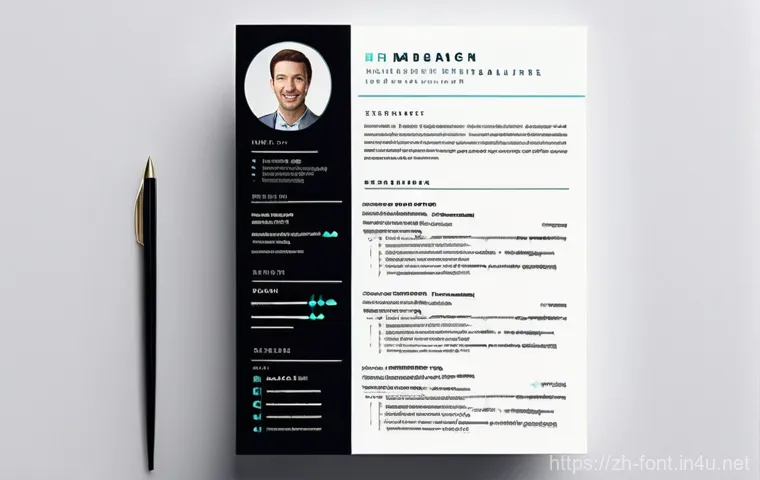
字体:你给HR的“第一印象”
亲爱的朋友们,你们有没有想过,一份简历投递出去,HR扫一眼可能就几秒钟?在这短短的时间里,除了你的内容,还有什么能瞬间抓住他们的目光,让他们愿意多停留几秒?我跟你说,字体!对,就是这个看似不起眼的小细节,它就像你的“无声名片”,默默地传递着你的专业度、品味,甚至是你对这份工作的重视程度。我有个朋友小李,能力明明很强,每次投简历却总石沉大海。后来我帮他一看,好家伙,简历上的字体五花八门,有卡通的,有艺术的,整个版面乱糟糟的,看得人眼花缭乱。我当时就跟他说,你这样投简历,HR第一眼就会觉得你不够严谨,甚至对工作缺乏基本的尊重。这可不是我胡说,这是我这些年看了无数简历,以及跟好几位资深HR朋友聊过之后得出的“血泪教训”啊!
别小看这些“小细节”:它藏着你的专业度
很多人觉得,字体不就是好看不好看嘛,内容才是王道。这话没错,内容当然重要,但是!如果你的“门面”就没收拾好,HR可能根本没兴趣深入了解你的“内涵”!你想想看,如果你收到一份字体模糊、大小不一、看着很费劲的简历,你会怎么想?是不是下意识就觉得这个人可能不太注重细节,做事有点随意?反之,一份排版整洁、字体清晰、阅读舒服的简历,哪怕内容暂时还没来得及细读,但第一印象就已经赢了。这背后传递的信息是:你是一个认真细致、有条理、注重专业形象的人。特别是在现在这个竞争激烈的求职季,每一个能让你脱颖而出的细节,都弥足珍贵。所以,选对字体,绝不仅仅是让简历“好看”那么简单,它更是一种无声的自我营销,帮你给HR留下一个专业且值得信赖的形象。
那些年我们踩过的“字体雷区”,你中招了吗?
“避之不及”的“非主流”字体
我们年轻人嘛,都喜欢追求个性,希望自己的简历能与众不同。但个性化和专业度之间,真的要找到一个微妙的平衡点。我见过太多朋友,为了“突出个性”,把简历弄得花里胡哨,用上各种奇奇怪怪的艺术字体,比如什么华文彩云、方正卡通、或者那种手写体。说实话,我自己看着都头疼,更别说每天要看上百份简历的HR了!这些字体虽然可能很“潮”,但它们最大的问题就是:阅读困难!你想想,HR是在高效筛选人才,不是在欣赏艺术品。如果你让他们的眼睛需要费力辨认每一个字,那你的简历很可能就会被毫不留情地刷掉。我有个朋友,学设计的,他想在简历里展现自己的创意,结果用了几种非常独特的字体。虽然他能力很强,但投出去的简历面试机会寥寥无几。后来我让他换回了常规的专业字体,面试机会一下子就多了起来。这就是活生生的例子,很多时候,你的“小心思”可能适得其反哦!
别让“艺术感”毁了你的专业度
除了那些过于花哨的艺术字体,还有一类字体也常常被我们“误用”,那就是一些系统自带的、显得有些老旧的字体,比如纯中文环境下的宋体。虽然宋体很经典,但在简历中,它会显得过于传统,缺乏现代感,不能很好地展现你的活力和与时俱进。当然,如果你应聘的是非常传统、严肃的行业,比如学术研究、文化遗产保护等,宋体或许还有一丝容身之地。但对于大部分现代企业,尤其是互联网、金融、科技、快消等行业,宋体真的会让你显得有点“落伍”。我真心建议大家在选择字体时,宁愿选择“平庸”的专业,也绝不要“出位”的业余。记住,简历是你的求职武器,它的首要任务是高效、清晰地传递你的信息,而不是展现你的字体收藏。下面我给大家整理了一个小表格,列举了一些常见的字体“雷区”和我的建议,希望大家都能避开这些坑:
| 字体类型 | 常见问题 | 建议 |
|---|---|---|
| 花哨艺术字体 (如:华文彩云) | 阅读困难,缺乏专业度,显得不成熟。 | 除非是设计类简历,否则坚决避免。 |
| 默认/系统老旧字体 (如:宋体/Times New Roman (纯中文环境)) | 缺乏现代感,略显沉闷和保守,无法突出个性。 | 可用现代感更强的无衬线体替代。 |
| 过小或过大的字体 | 过小易造成阅读疲劳;过大显得排版粗糙,浪费空间。 | 正文建议10-12pt,标题14-16pt。 |
HR眼中加分的“王牌”字体,你知道几个?
清晰易读:简历字体的“黄金法则”
既然知道了哪些字体不能碰,那我们接下来就得聊聊,到底哪些字体才是HR们真正喜欢、甚至能给你的简历加分的“王牌”选择。我的经验是,无论你应聘什么职位,清晰易读永远是简历字体的“黄金法则”。想象一下,HR每天要处理大量的简历,他们最需要的就是一眼就能抓住重点,快速获取信息。所以,那些笔画清晰、结构稳定、辨识度高的字体,自然会成为首选。在中文简历中,我强烈推荐大家使用微软雅黑、思源黑体(Noto Sans CJK)和方正兰亭黑。这几款字体都是现代感十足的无衬线字体,字形简洁大方,在屏幕上和打印出来都非常清晰。我之前帮好几个朋友改简历,仅仅是把字体统一成微软雅黑,整个简历的专业度就瞬间提升了好几个档次,他们自己都惊叹效果这么明显!
国际范儿与本土化:中英文字体搭配秘籍
对于有英文内容的简历,或者需要展现国际范儿的求职者来说,中英文字体的搭配就显得尤为重要了。很多时候,我们会直接用一个中文字体,然后英文部分就跟着一起变,结果不是英文看着别扭,就是中文显得不协调。其实,最理想的做法是为中文和英文选择各自最合适的字体,并且确保它们风格统一。英文部分,我通常推荐使用Arial、Calibri、Lato、Open Sans或者Roboto。这些都是非常经典的无衬线字体,简洁、专业、易读,而且在国际上通用度很高。比如,你可以选择中文用微软雅黑,英文用Calibri,它们都是现代无衬线体,搭配起来非常和谐,看起来就像是精心设计过的一样。我记得有一次,我参加一个跨国公司的招聘会,当时就听到HR提到,他们更偏爱那些中英文排版统一、看起来“舒服”的简历。所以,别小看这个搭配,它可是能悄悄帮你加分,让你在国际化的背景下也显得游刃有余!
字体大小和行距:别让“视觉疲劳”拖垮你的简历
大小适中:简历阅读舒适度的秘密
选对了字体,这只是成功的第一步。接下来,字体的大小和行距,这两个细节,同样能决定你的简历是让人“赏心悦目”还是“望而生却”。我发现,很多朋友在排版简历时,要么字号太小,密密麻麻挤成一团,让人看得眼睛疼;要么字号太大,几句话就占满一页,显得内容空洞,不够充实。这两种情况都会给HR带来视觉疲劳,甚至觉得你不懂得如何合理利用空间。我的建议是,简历正文的字体大小一般选择10到12pt(磅)为宜。这个尺寸在大多数屏幕和打印件上都清晰可辨,既不会太小导致阅读困难,也不会太大显得笨拙。当然,你的姓名、联系方式这些重要信息,以及各个板块的大标题,可以适当放大一点,比如14到16pt,这样能更好地突出重点,让HR一眼就能抓住关键信息。我曾经帮一个朋友调整简历,他原本的字号统一都偏小,我给他调整了合适的字号,并把重要信息加粗放大,他再看自己的简历,都觉得瞬间变得清晰明朗,阅读体验好了不止一星半点!
行距与段落:打造“呼吸感”的版面
除了字体大小,行距和段落间距也是打造一份“呼吸感”简历的关键。什么叫“呼吸感”?就是让你的简历看起来不会那么拥挤,文字之间、段落之间有足够的留白,让HR的眼睛在阅读时能得到适当的休息。如果行距太窄,文字就会挤在一起,形成一大块密不透风的“墙”,阅读起来非常吃力。而如果行距太宽,又会显得过于松散,浪费宝贵的版面。通常情况下,我建议简历的行距设置在1.15到1.5倍之间,具体可以根据你的内容多少和整体排版效果来微调。另外,每个段落之间最好能留有适当的间距,或者首行缩进,这样能让简历的结构更清晰,逻辑层次一目了然。我之前在帮一位应届生朋友修改简历时,发现他的简历内容不少,但排版非常紧凑,一行接一行,让人觉得喘不过气。我帮他把行距和段落间距稍微调大了一点,整个简历瞬间变得清爽起来,内容也显得更有条理了。所以,别以为这些只是小事,它们可是直接影响HR阅读体验,进而影响你简历命运的关键细节哦!
中英文简历混排:如何做到“浑然天成”?
字体的“家族联姻”:选择同源或风格相似的字体
在很多跨国公司或者国际化背景的求职中,一份中英文混排的简历是必不可少的。但你知道吗,中英文混排其实是个技术活,如果搭配不好,整个简历就会显得非常割裂,甚至有点“精分”。最常见的误区就是中文部分用一个字体,英文部分用另一个风格完全不同的字体,导致视觉上非常不协调。我的秘诀是,尽量选择那些“家族联姻”的字体,也就是同源字体家族,或者风格非常相似的字体。比如,前面提到的思源黑体(Noto Sans CJK),它其实是一个包含了中日韩等多语言字体的超级字体家族,它的英文部分和中文部分的字重和风格都非常统一。你用它来排版中英文简历,效果会非常和谐自然,就像天生一对一样。如果找不到同源字体,那也要选择风格近似的,比如中文用微软雅黑,英文用Arial或者Calibri,它们都是现代无衬线体,简洁大方,搭配起来也能做到“浑然天成”。我亲身体验过,用对这种“家族联姻”的字体,能让你的简历看起来更加专业、有设计感,HR一看就会觉得你是个注重细节、有品位的人。
避免“水土不服”:中英文混排的常见误区
除了字体的选择,中英文混排还有一些常见的“水土不服”的误区需要大家注意。第一个就是大小不一。很多时候,中文和英文在同样的字号下,视觉大小可能会有差异,如果直接照搬,可能会导致某一部分显得过大或过小。所以,排版时一定要肉眼观察,进行微调,确保中英文的视觉大小平衡统一。第二个误区是,很多人会把英文部分的标点符号也跟着中文标点一起处理,比如使用全角标点。但在英文语境下,应该使用半角标点。这种小细节虽然不影响阅读,但却能体现你是否真的懂得国际化的标准和规范。我记得之前有个朋友,他的英文简历里用了大量的全角逗号和句号,我当时就提醒他要改过来。改完之后,整个英文部分看起来就地道多了。所以,在处理中英文混排简历时,一定要注意这些细节,它们不仅关乎美观,更关乎你的专业素养和国际视野的展现。记住,一份完美的简历,是每一个细节都经得起推敲的。
你的简历,真的“读”起来舒服吗?
白纸黑字的“艺术”:对比度与背景色
字体选对了,大小和行距也调好了,是不是就万事大吉了?别急,还有个常常被大家忽略的关键点——对比度!你的简历虽然是“白纸黑字”,但这“白”和“黑”之间,其实也藏着大学问。想象一下,如果你的文字颜色太浅,或者背景色不是纯白,再好的字体也会变得模糊不清,阅读体验大打折扣。所以,我给大家的忠告是:除非你是设计师或者应聘非常强调视觉创意的职位,否则请务必保持简历的“高对比度”原则——黑色文字搭配纯白背景,这是最清晰、最专业的组合,没有之一!我曾看到一些简历,为了追求“文艺范”,把背景弄成浅灰色,或者文字用深灰色,结果在屏幕上看还行,一打印出来就惨不忍睹,模糊得像没墨了一样。HR看到这种简历,大概率会觉得你不够认真,或者压根没考虑过他们的阅读感受。别让这些“小聪明”成了你求职路上的绊脚石。
问: 我该如何在简历中应用这些字体,才能让它看起来既专业又舒服,同时又能避免格式问题呢?
答: 这绝对是个实用到爆炸的问题!选对了字体只是第一步,如何正确应用,让它发挥最大的效果,才是关键!我来教你几个我“屡试不爽”的技巧:第一,全篇字体保持统一和简洁。 很多人喜欢在简历里用好几种字体,以为这样能突出重点,但结果往往是适得其反,让简历看起来杂乱无章。我建议大家,整份简历的中文部分最多用1-2种字体,英文部分也控制在1-2种。比如,标题用一个略粗的字体,正文用一个常规字体,保持整体风格的协调统一,这样看起来既专业又舒服。你可以大胆地尝试用微软雅黑作为中文主字体,英文部分搭配一个Arial或者Calibri,效果绝对棒!第二,字体大小要适中。 正文内容通常使用10-12号字,标题可以适当放大1-2号,或者加粗,但不要太大,以免显得突兀。行距也要设置得疏朗一点,别让文字挤在一起,这样HR阅读起来眼睛才不会累。我发现很多小伙伴为了多塞内容,把字号调得特别小,密密麻麻一大片,HR一看就头疼,根本没耐心仔细读。所以,学会“留白”,让你的简历“呼吸起来”也很重要!第三,最关键的一步,导出PDF格式! 这是一个避免格式错乱的“神操作”!不管你在Word、Pages还是其他什么软件里制作简历,最终提交的时候,一定要把它导出为PDF文件!为什么呢?因为PDF文件会将你使用的字体“嵌入”进去,这样无论HR用什么设备、什么系统打开你的简历,看到的字体样式都会和你制作的时候一模一样,不会出现字体缺失、格式跑偏、乱码等让人抓狂的问题。我以前就有过简历发出去结果HR那边字体显示不出来,变成默认字体,导致排版全乱的“血泪教训”,所以现在我每次都会再三确认是不是PDF格式,而且会自己打开检查一遍。这一个小小的步骤,真的能帮你省去很多麻烦,也能确保你的完美简历能被HR完整地看到!